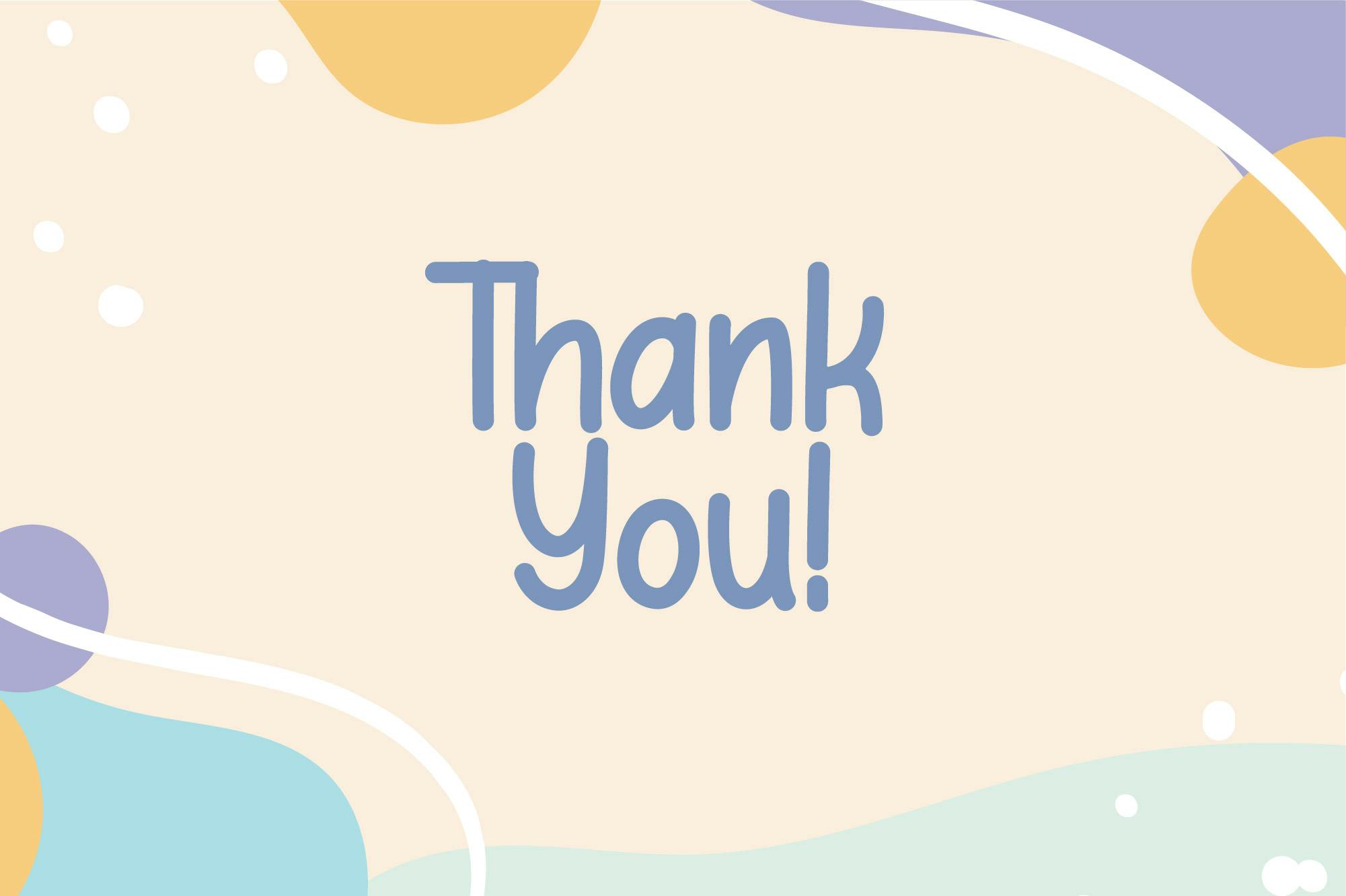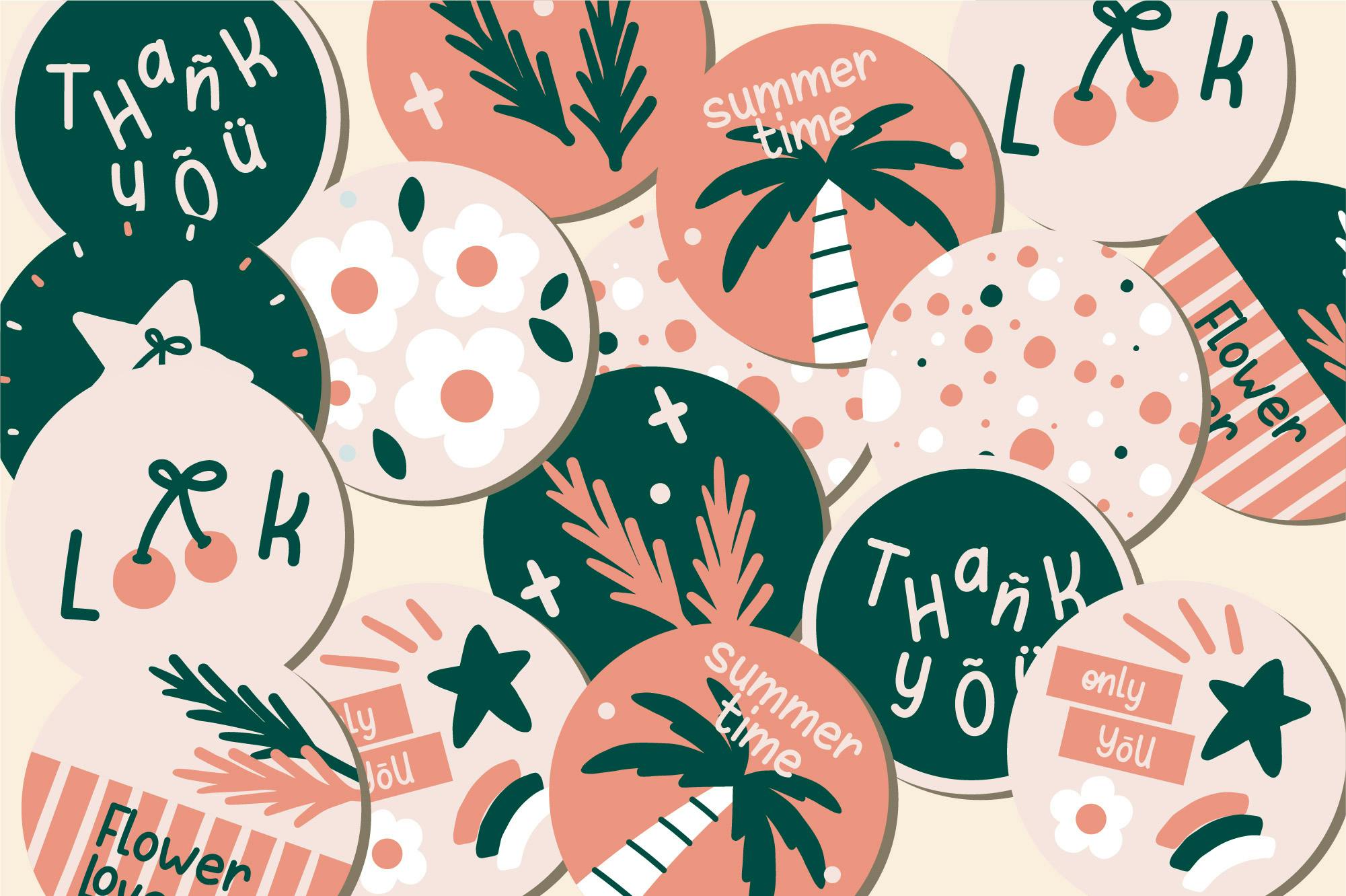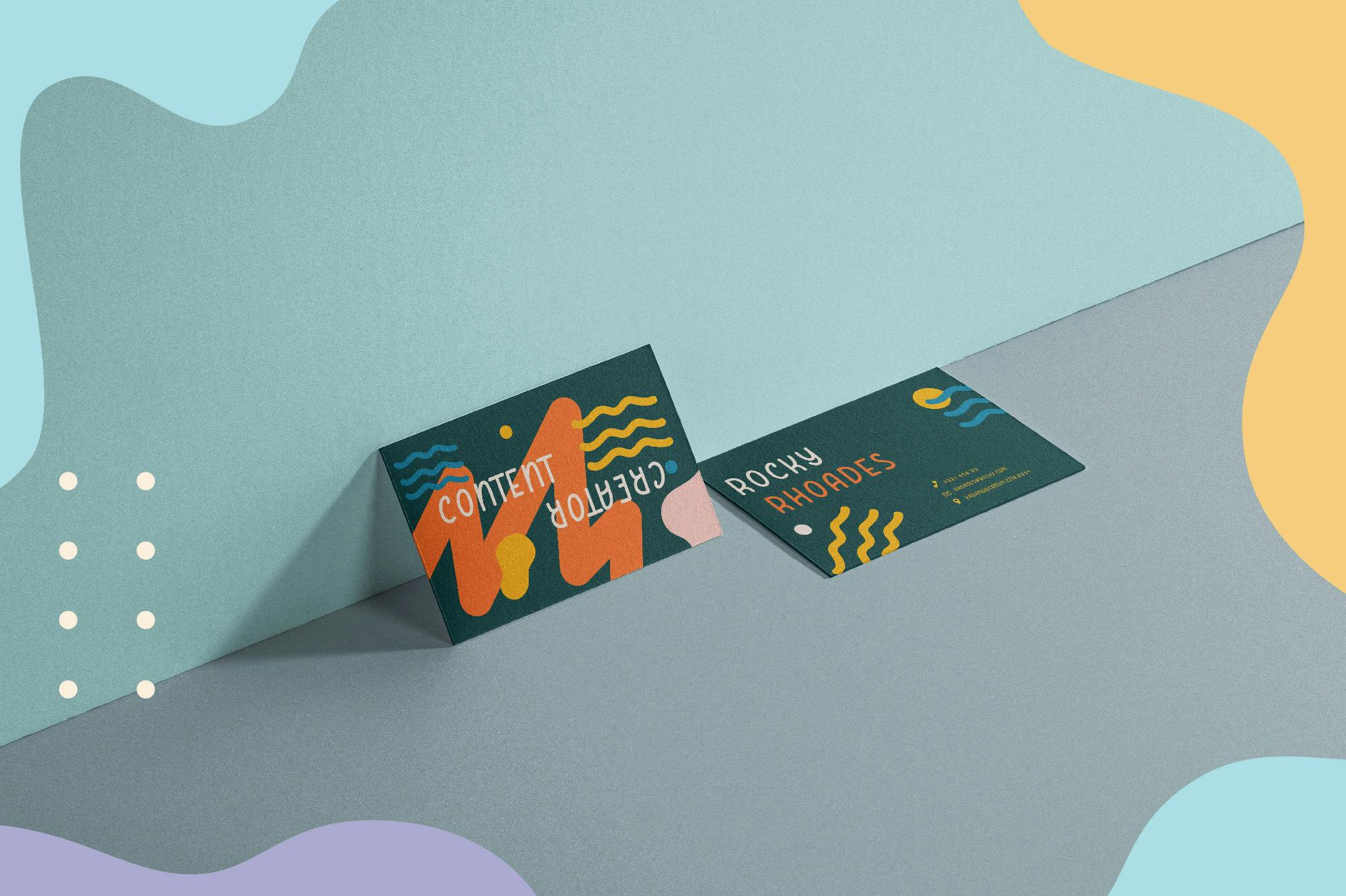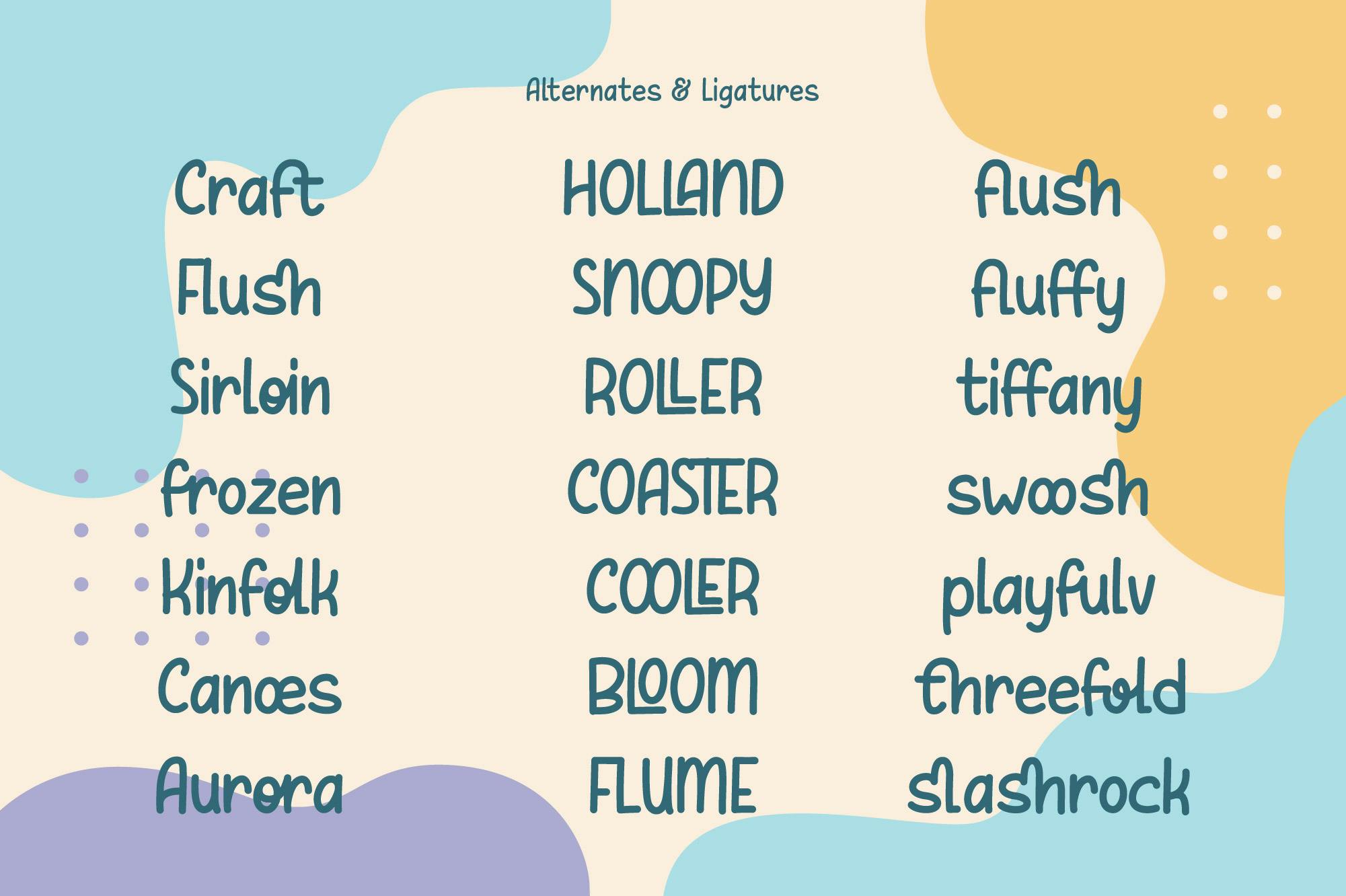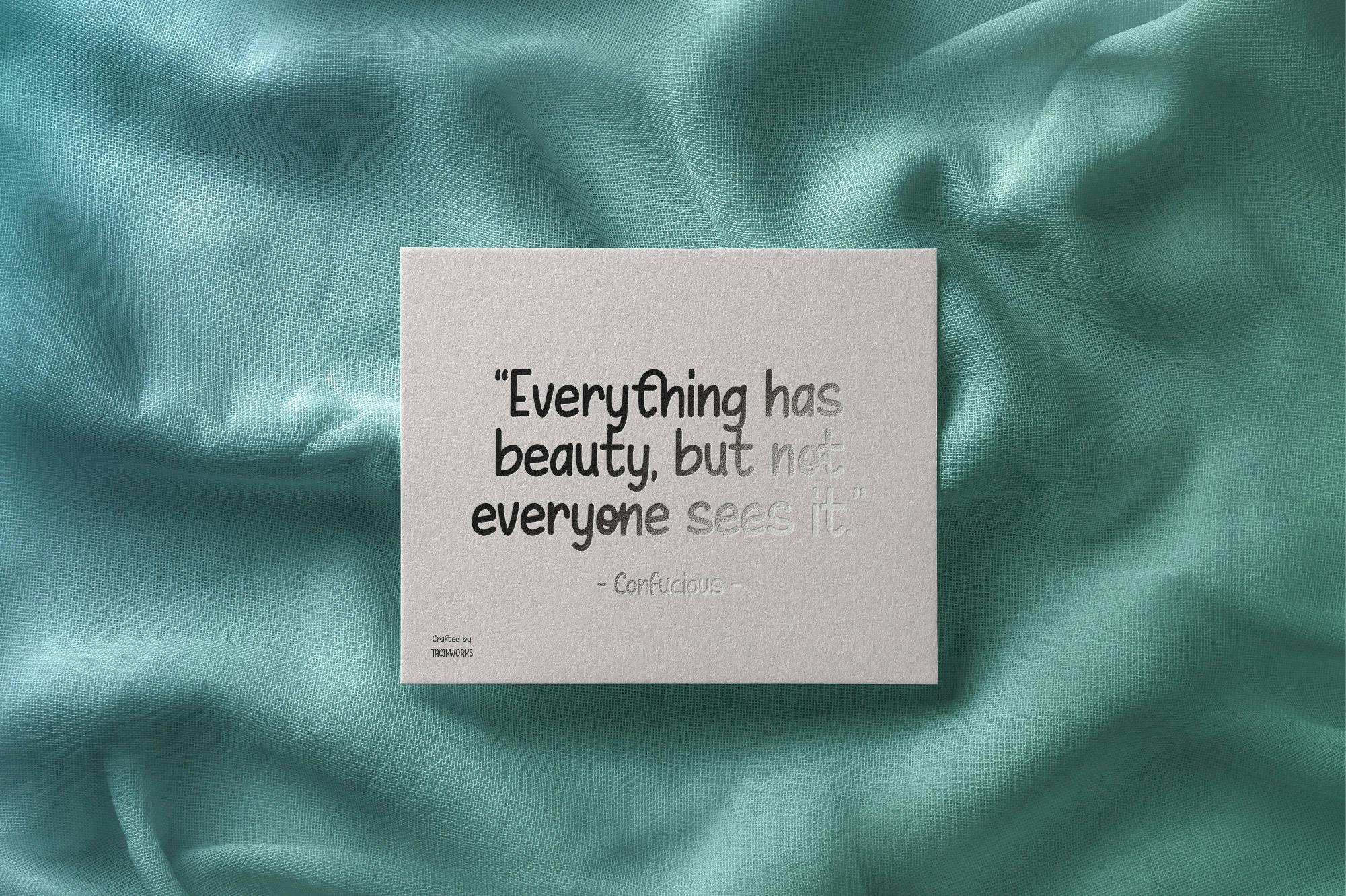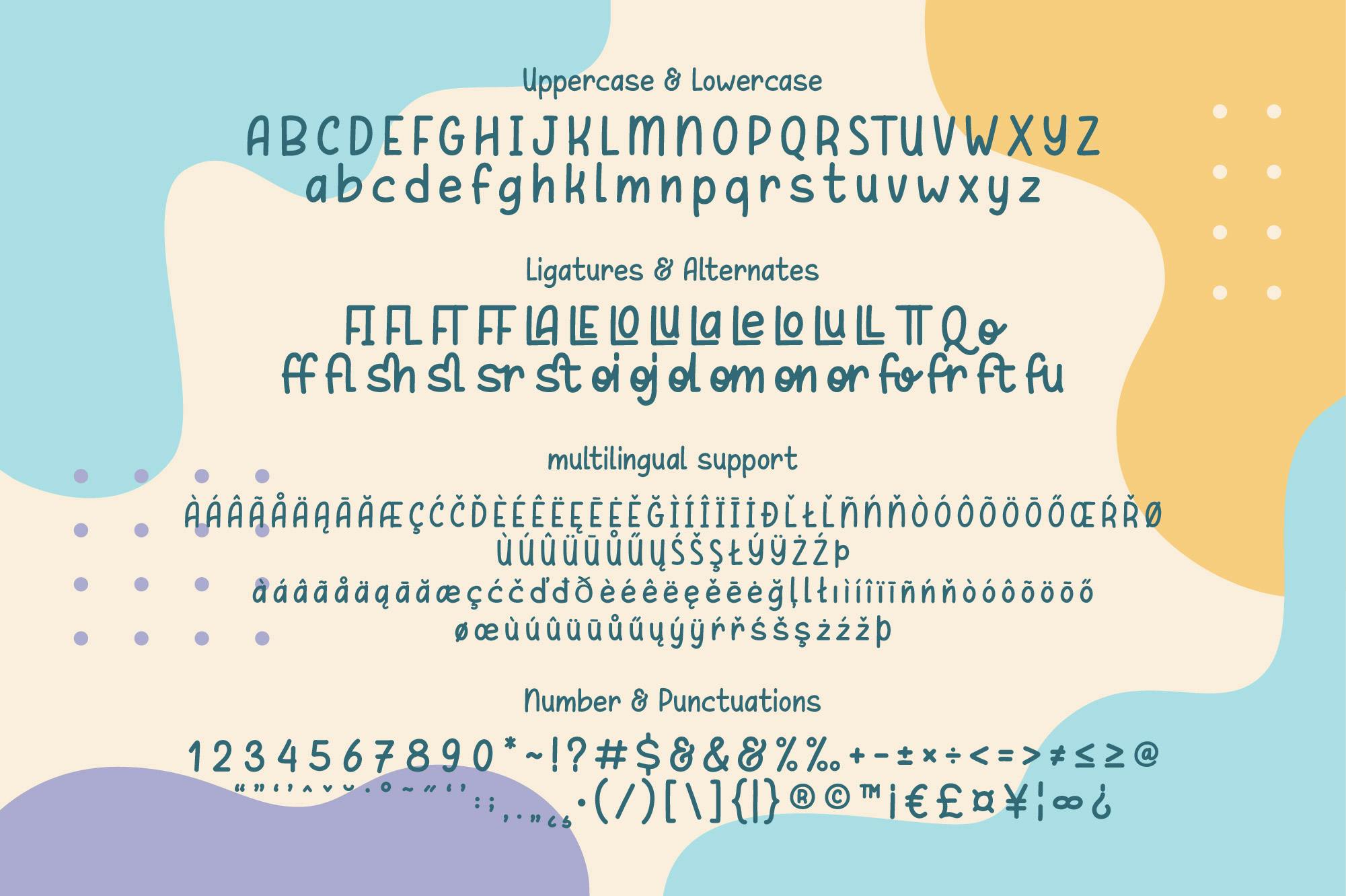
فونت Lovely Crafter الهامگرفته از نوشتار با خودکار مارکر است که شکلی ساده و خطی دارد و به همین دلیل یک فونت ساده و زیبا ایجاد میکند. این فونت شامل حدود 279 کاراکتر گلیف از جمله حروف بزرگ، کوچک، لیگاتورهای اختیاری و لیگاتورهای استاندارد است. این فونت برای طراحیهای وینتج مانند پوسترها، کالاهای تبلیغاتی، لباس، بروشورها، کارتهای ویزیت و سایر پروژهها مناسب است.
این فونت دارای PUA unicode است (فونتهای ویژه کدگذاری شده) که به طراحان و صنعتگران این امکان را میدهد تا به راحتی به تمام کاراکترهای جایگزین دسترسی پیدا کنند.